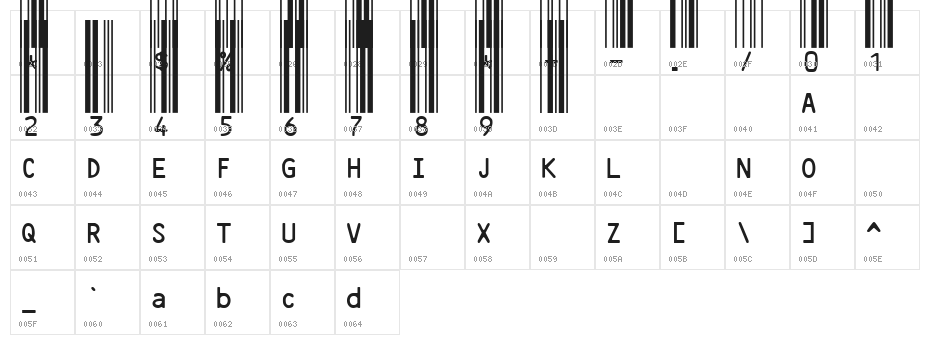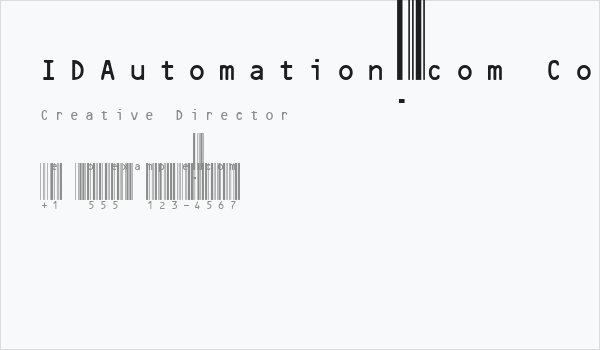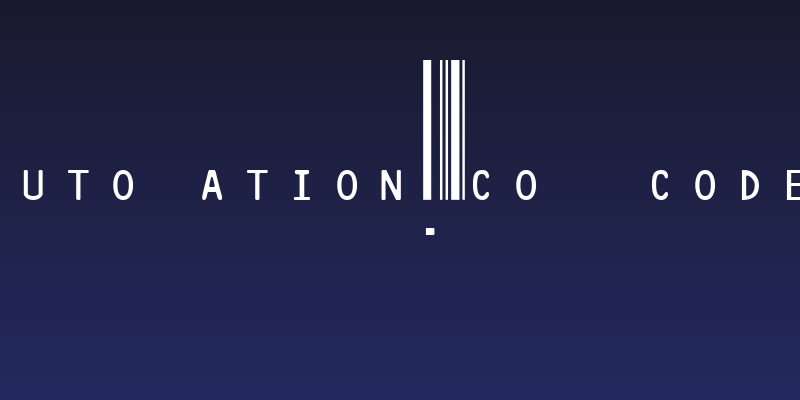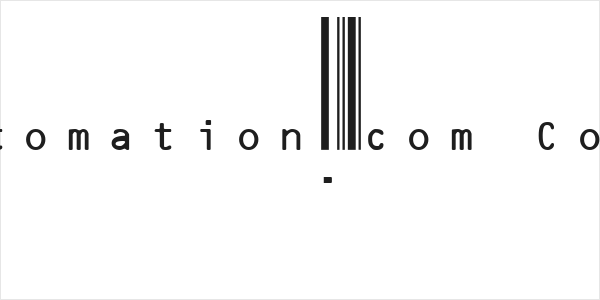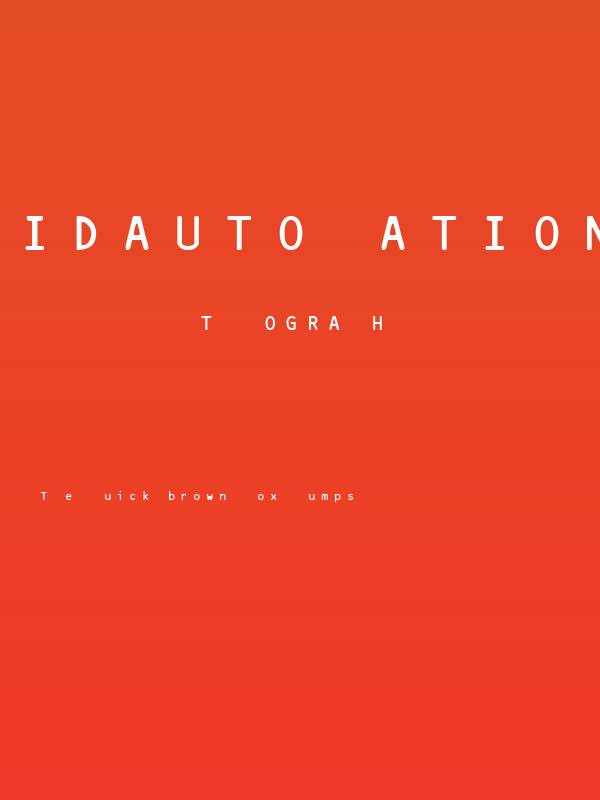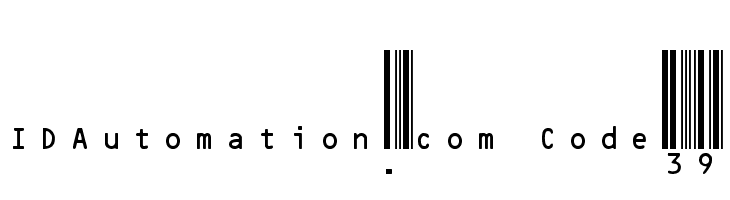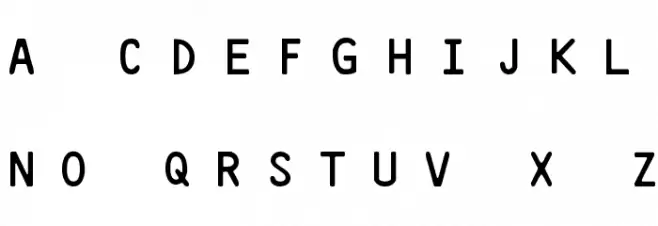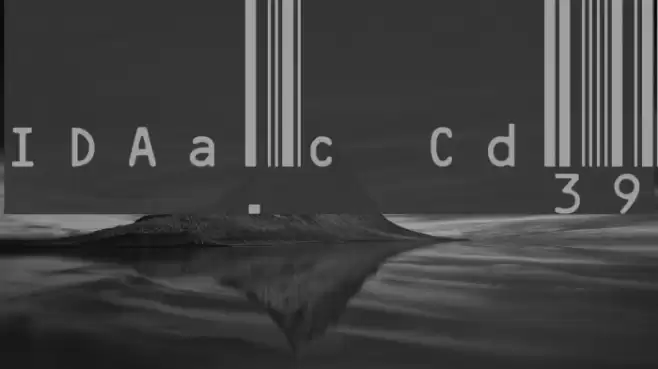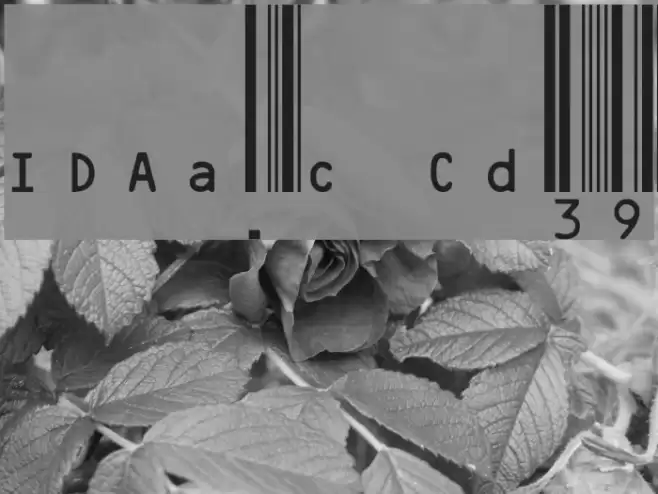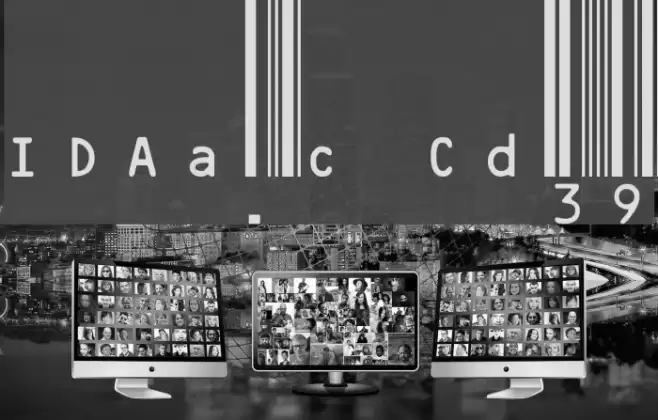
IDAutomation.com Code39 Font
| Style général | Technical |
| Cas d'utilisation | Barcodes, Technical documentation |
| Projets proposés | Ideal for creating barcodes for inventory systems, product labeling, and logistics management. |
IDAutomation.com Code39